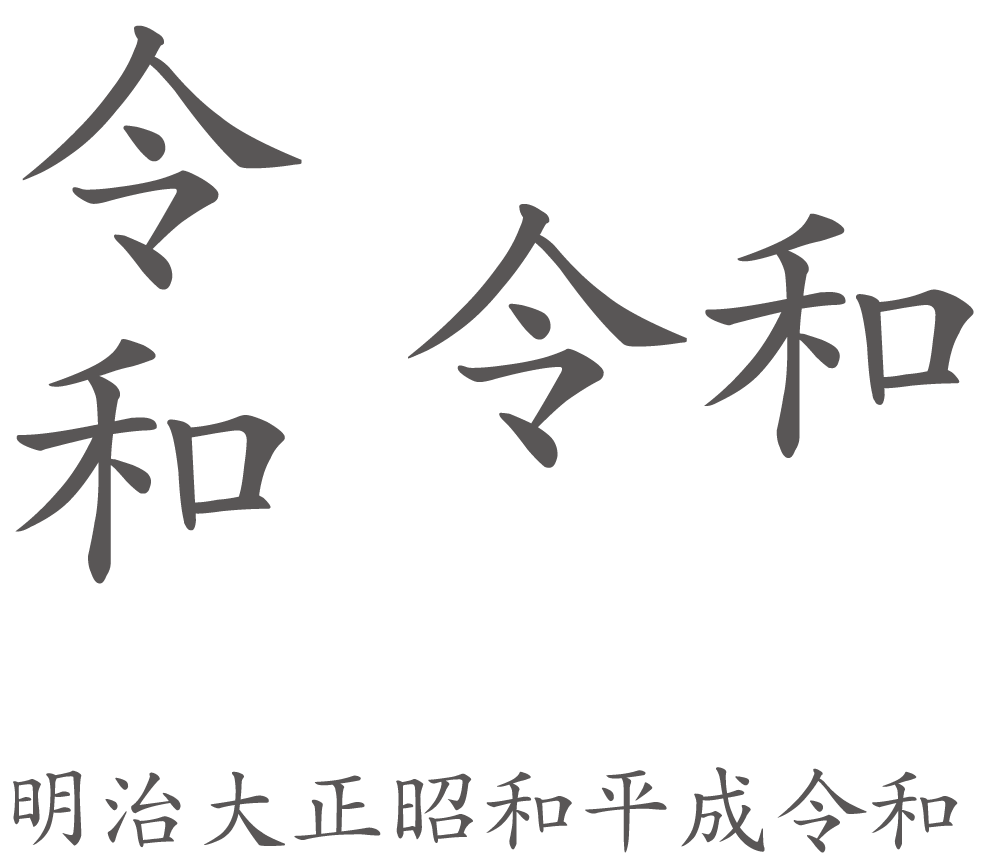
現代の漢字の基本系となる書体「楷書体」
現代の漢字の基本系といわれる。一画ずつ離して書く。
上記で使用した書体はダイナフォントの中楷書体。
新元号「令和」楷書体書体見本
新元号「令和」の楷書体の書体見本。
「綾鷹」のタイトルにダイナフォント「中楷書体」が採用
コカ・コーラ社のお茶ペットボトル「綾鷹」のタイトルにダイナフォント「中楷書体」が採用されている。